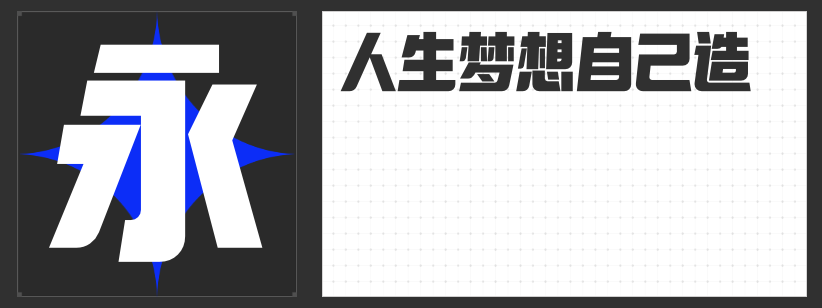
创意设计新势力:四款突破常规的字体美学探索
在视觉设计的多元宇宙中,字体不仅是文字的载体,更是情感与创意的具象化表达。以下四款精心设计的创意字体,以独特的结构语言与视觉张力,为设计作品注入鲜活的生命力。
一、励字逆反差圆舞简
这款字体以逆反差设计为核心,突破传统字体的视觉平衡法则。圆弧饱满的笔画处理赋予文字灵动韵律,粗细对比强烈的线条在理性与感性间游走。中宫的精准把控与重心稳定结构,使其既适合动态标题的视觉冲击,亦能承载正文排版的秩序感。弧形笔画与直线框架的碰撞,形成独特的视觉记忆点。
二、励字跨界黑简 超级黑
将几何理性与曲线美学进行先锋融合,这款字体以90%的字面率构建视觉张力场域。粗壮的直线笔画奠定力量基调,流畅的曲线元素则注入灵动气质。钩笔画与弯钩的微妙抬升处理,配合斜切收笔的动态平衡,在保持文字识别性的同时,创造出充满呼吸感的视觉层次。块面化设计使其成为标题设计的理想选择。
三、励字造梦简 超粗
灵感源自城市天际线的透视美学,这款字体以不对称结构演绎空间张力。左侧倾斜与右侧竖直的对比构图,配合夸张的透视比例,模拟出仰望摩天楼的视觉震撼。圆润的转角处理与留白设计,在棱角分明的字形中注入萌动气质,形成刚柔并济的独特视觉语言。
四、高手庆科智雅体 大黑
以直线构建的理性框架中,这款字体通过连笔折笔的灵动处理打破机械感。切口工艺的精细运用优化了视觉锐度,中宫布局的黄金比例确保阅读流畅性。西文字符的切角设计与中文形成风格共振,在保持功能性的同时,创造出具有现代主义美感的视觉系统。
这四款字体以不同维度突破传统字型框架,在保证功能性的前提下,为设计语言注入更多可能性。无论是追求视觉冲击的标题设计,还是需要层次表达的排版系统,它们都能以独特的结构美学,为创意作品构建更具辨识度的视觉基因。